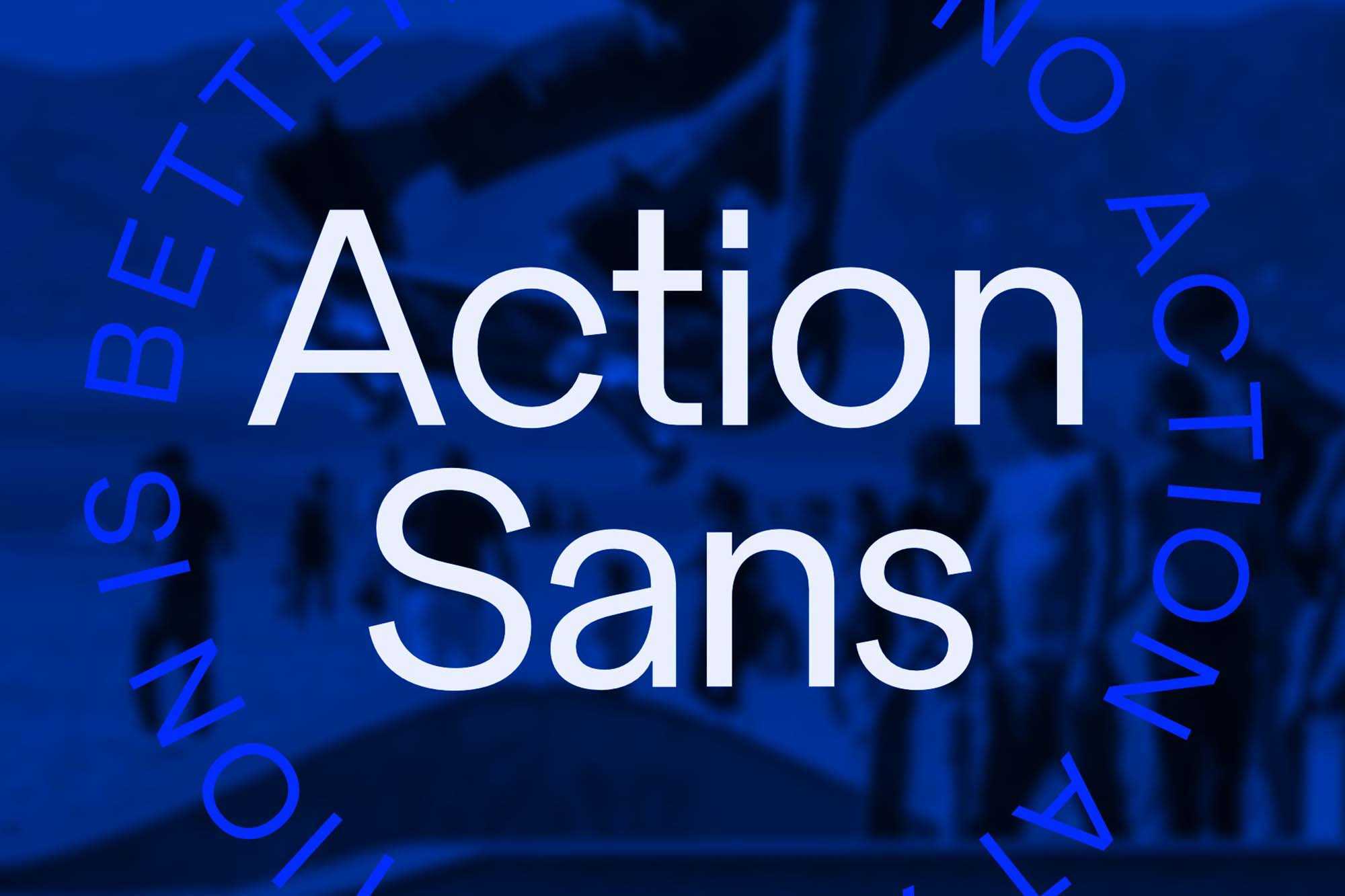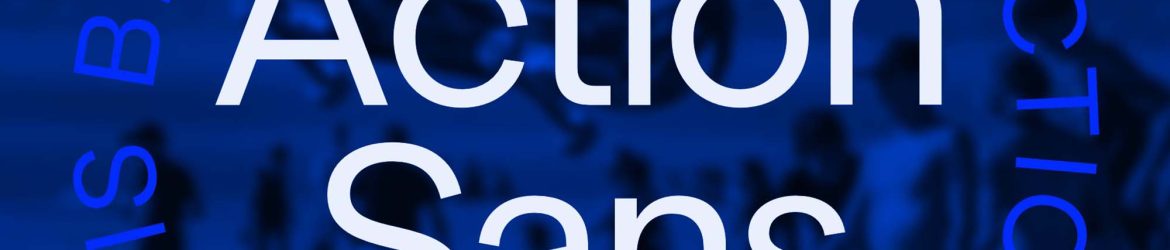
A fonte ‘Action Geometric Sans Font’ carrega consigo as marcas da lei de ação-reação de Newton, onde para cada ação surge uma reação. Este recurso gráfico representa a fonte geometrica sans que a Hanken Co. apresenta, prometendo despertar tanto a curiosidade dos leitores quanto do design. Com formas geométricas e linhas retas, esta fonte se destaca pelo seu equilíbrio e simplicidade. Seja você um designer ou leitor, o impacto desta fonte é inevitável. Ela não apenas enriquece a sua experiência visual, mas também contribui para a criação de um layout atraente e funcional. Seja a sua paleta de cores, seja a forma que escolher, a fonte ‘Action Geometric Sans Font’ certamente irá transformar seu trabalho.